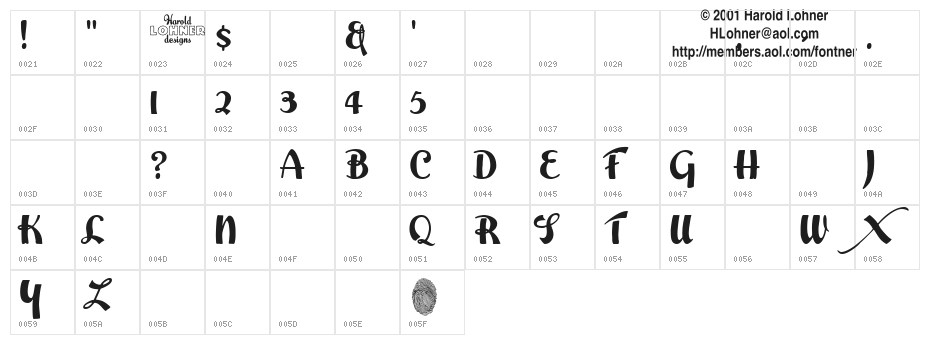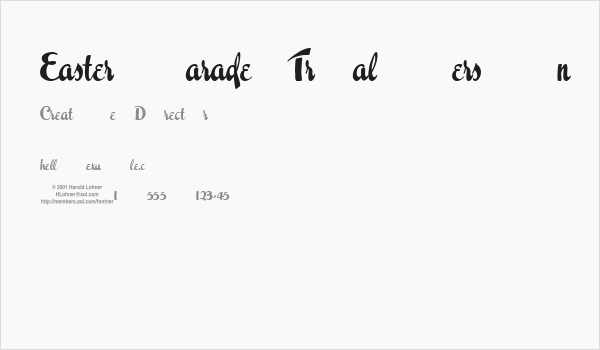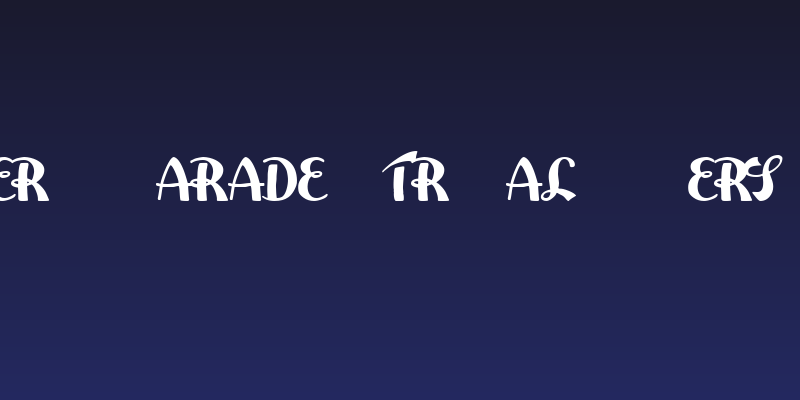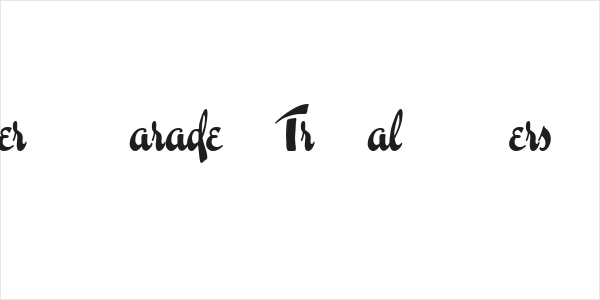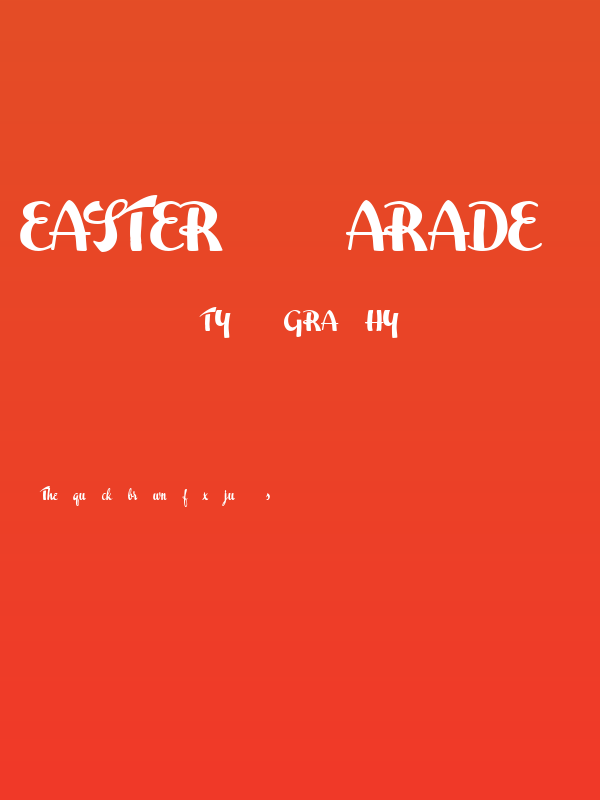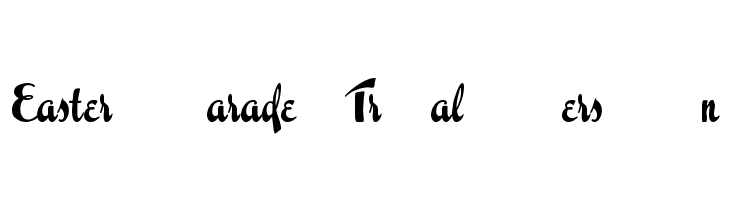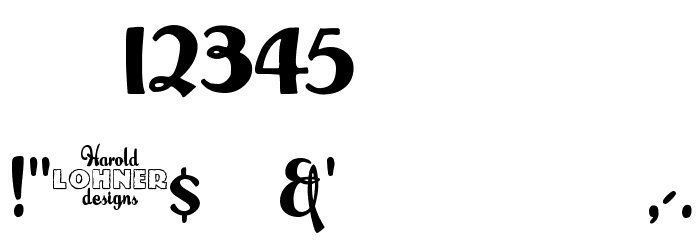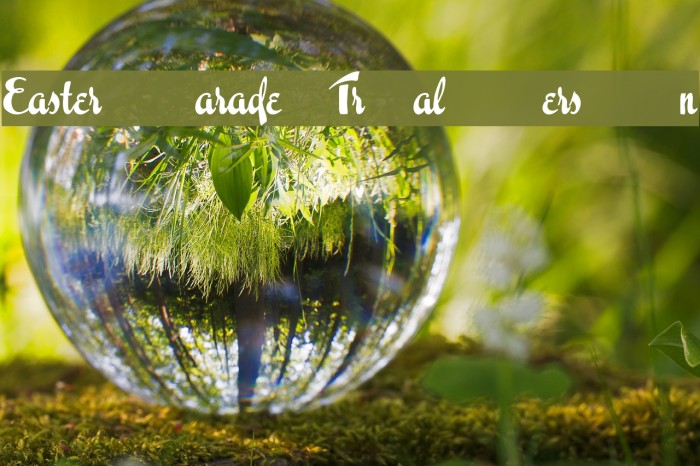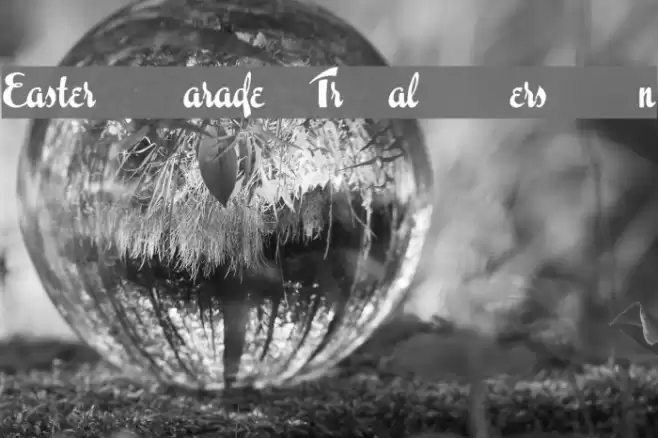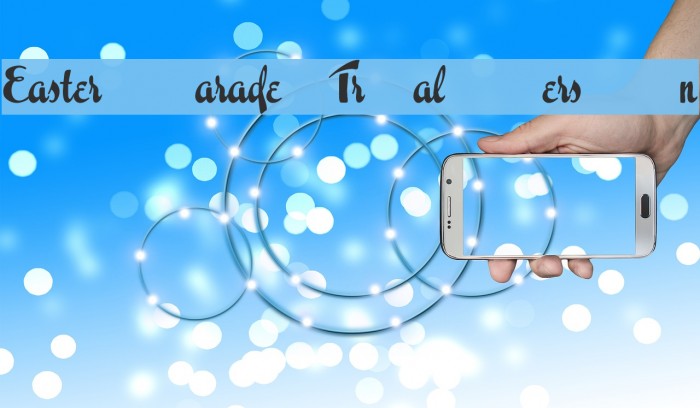
Easter Parade Trial Version Font
| Anwendungsfall | Headlines, Logos, Invitations |
| Vorgeschlagene Projekte | Ideal for invitations, greeting cards, festive banners, and vintage-themed designs. |